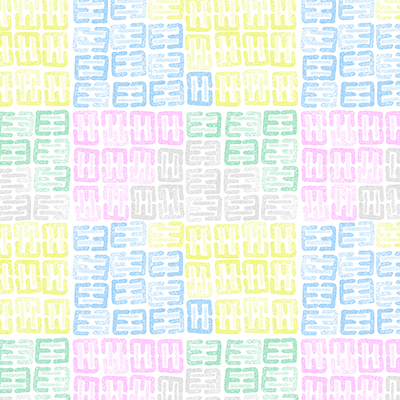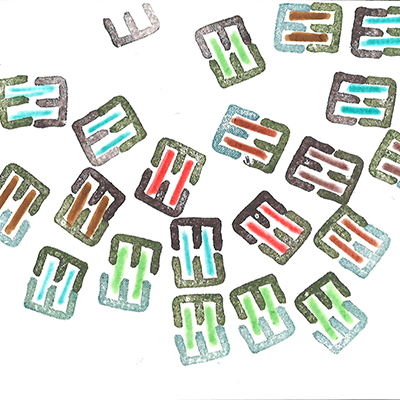
タイルの整列
淡い色のグラデーションがどこかリズミカルなタイルの整列
Artist井上 寿士
Designer樋野 康二
Organizationフォーラムひこばえ
ローマ字にしたときの、ひこばえの頭文字 H 、ひこばえの最後の文字E を重ね合わせてこのような形となりました。(井上 寿士)
HとEで構成されたスタンプのようなモチーフをタイルのように並べてみました。今回は淡いトーンで着色していますが、好みに合わせて色や配置を変えることができるパターンです。(樋野 康二 )